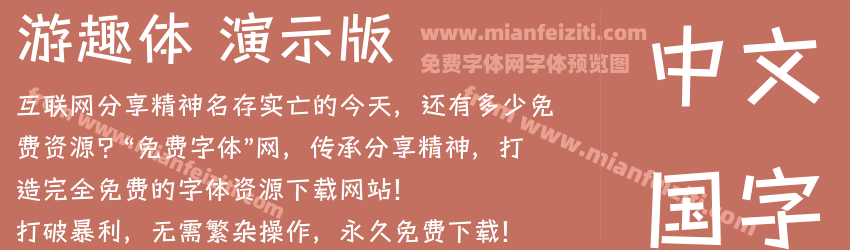
游趣体因笔形像笔杆一样以直线设计,而被视为一款既可爱调皮,亦有田园写意风格的字体,本人基于 Fontworks 出品的日文字体ステッキ / Stick 扩充、调整字形,并编辑、适当增加 OpenType 特性,以满足简体中文的使用需求。
补字计划
简体部分
目标字汇①范围内修改 G 形②;
增补原字库中含有的繁体字对应的简化字;
义务教育语文课程常用字表 3500 字;
GB/T 2312-1980 汉字部分 6763 字;
通用规范汉字表 8105 字;
现代汉语通用字表 7000 字;
按需添加一些表外字,参照「霞鹜开源字体外字初步整理一览表」第一部分。
① 包括《义务教育语文课程常用字表》(以下简称《义务教育常用字表》)、GB/T 2312-1980、《现代汉语通用字表》《通用规范汉字表》。
② 修改范围包括《义务教育常用字表》、GB/T 2312-1980、《现代汉语通用字表》《通用规范汉字表》,部分字形差异视为设计特性,不做修改,如「厶」「幺」「亥」等字。
繁体部分
由于该字体目前定位仍以简体为主,目前无对原字体包含的繁体部分增补及修改的计划。